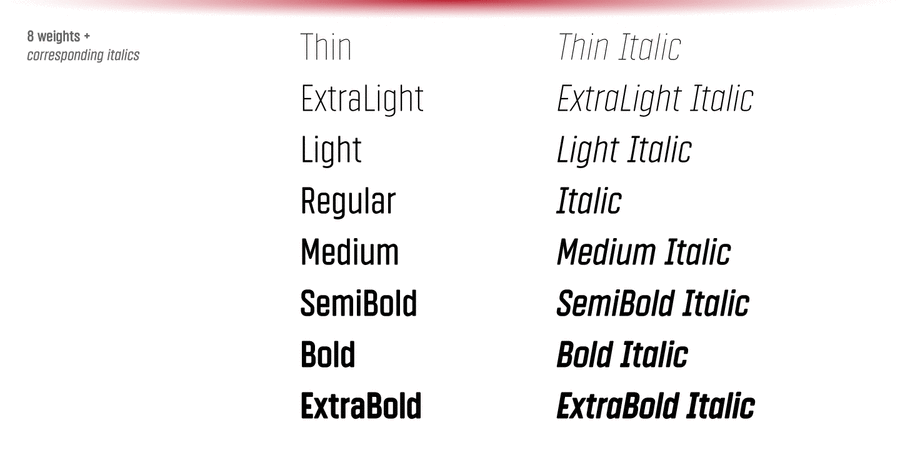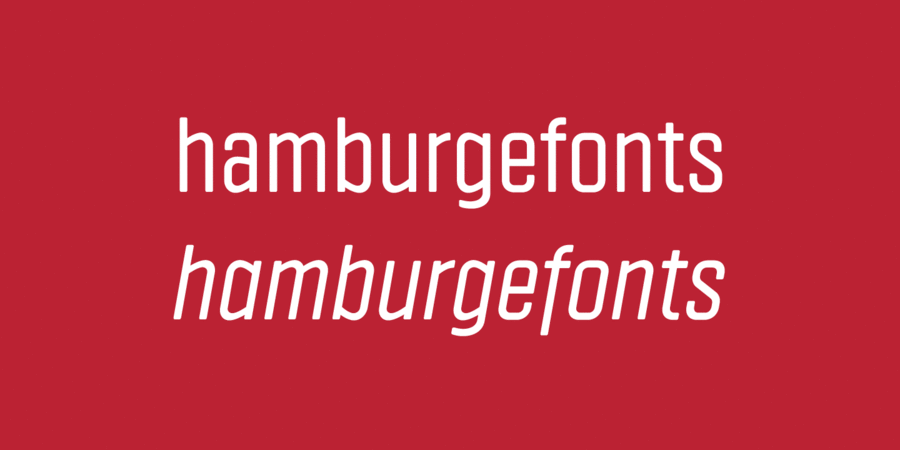
Опис гарнітури Vin Sans Pro – вузький жорсткий ґротеск зі збільшеним x-height та заокругленими кутами, призначений для коротких текстів. Vin (він) – супергарнітура з трьох маскулінних шрифтових сімейств з яскраво вираженими вертикалями, прямокутними овалами та заокругленими кутами. Для більшої виразності всі три шрифти мають збільшену висоту рядкових. Шрифт розробив Олег Ліщук у студії Mint Type у 2018 році.
Особливості сімейства шрифтів Vin Sans ProХіт десятиліття:
Асоціації з сімейством шрифтів Vin Sans ProОсобистість і характер гарнітури:
неоновий, точний, футуристичний, рівний, прямокутний, тонкий, статичний, логічний, холодний, легкий, міський, сучасний, інженерний, урбаністичний, креслярський, скляний, крихкий, прозорий, спокійний, дротяний, худий, стійкий, автоматичний, техногенний, твердий, чіткий, машинний, космічний, тісний, стиснений, стабільний, серйозний, практичний, прагматичний, технічний, якісний, міцний, надійний, впевнений, переконливий, авторитетний, відповідальний, гучний, важливий, наполегливий, ігровий, сильний, індустріальний, крутий, амбітний, суворий, важкий, сталевий, залізний, гарячий, монументальний
фантастика, гаджет, девайс, креслення, архітектура, інженер, Місто, електроніка, прилад, наука, айтішник, айті, IT, технології, космос, конструктор, автоматика, урбаністика, дизайн, техніка, гра, авто, шутер, екшен, кінотеатр, Футбол, лего, іграшка, спорт, промисловість, верстат, інструмент, електростанція, енергетика, завод, тренажери, ремонт, блокбастер, бойовик, селфі, паливо, кіно, нафта Гарнітура асоціюється з віком: